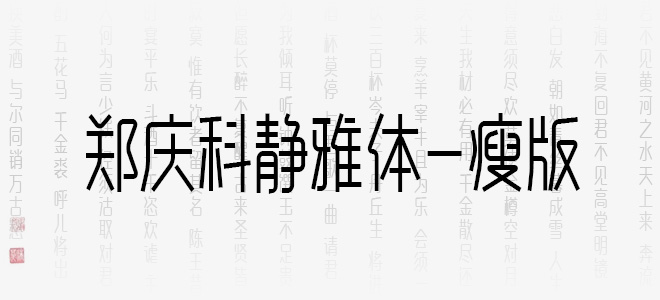
鄭慶科靜雅體-瘦版是一款中文藝術(shù)字體,這款字體是由鄭慶科靜雅體修改而成,每一個(gè)字體都顯得很是細(xì)長(zhǎng),包含大陸簡(jiǎn)體漢字6763個(gè)、英文大小寫52個(gè),阿拉伯?dāng)?shù)字10個(gè),以及682個(gè)符號(hào),適合應(yīng)用于藝術(shù)設(shè)計(jì),平面宣傳設(shè)計(jì),網(wǎng)頁(yè)設(shè)計(jì),海報(bào)設(shè)計(jì)等領(lǐng)域,需要的朋友可以前來本站下載。
鄭慶科靜雅體-瘦版 中文字體